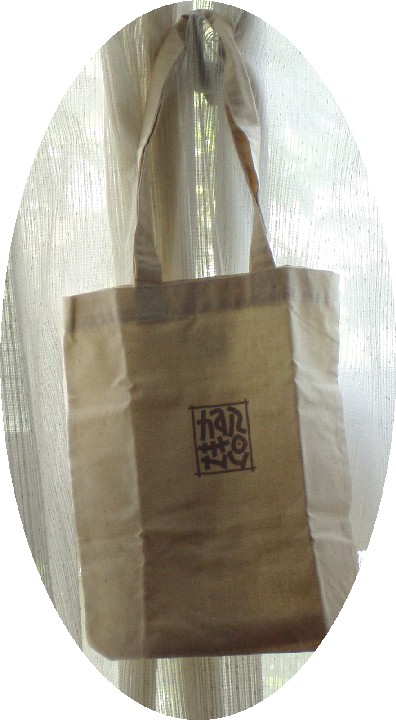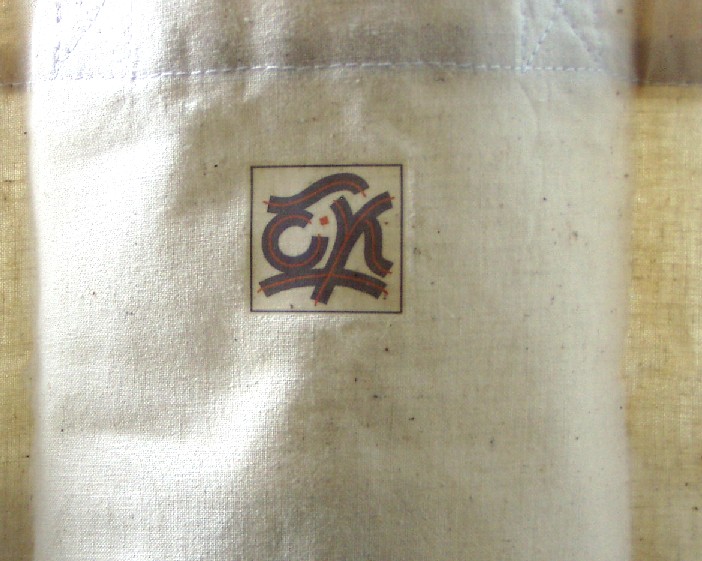
作品展の戦利品その1
京橋のギャラリークボタで行われている「アルファ・クラブ作品展」は、お天気のバックアップもあり、たくさんの人に訪れてもらっています。
ずいぶんと長い時間をかけて見てくださっている方が多く、作品の前で話しがはずんでいる様子を見ていると、何だか心が温かくなるものですね(外は暑いですが)…。
さて今回は、初試みでカリグラフィーを使ったグッズの販売も行っています。
ギャラリーショップと名づけた小さな空間は、みんなのアイデア満載の小さなものたちで一杯です!クオリティーは高いですよ!
この空間に足を踏み入れたら…あれもこれもと皆さん迷われて
手に一杯つかんでいる方も…。もしかして、ここが一番滞在時間が長かったりして…。
みんなが楽しそうに買っているので…裏方の私も最初はお客様優先で…と見守っていたのですが、とうとう手が…でてしまったの
でした〜。
カード類以外に、布物もたくさん出ています。Tシャツ、エプロン…。
そして、私が欲しかったのはこの小さな袋です。A4がちょうどおさまる程のかわいい袋です。
こういう大きさの袋はバッグにたたんで入れておけるし、便利なんですよね〜。しかもこの両面についたオリジナルのマークが素敵!
即、ゲットです。
そして、癒しの手書きのカード!
繊細な水彩カラーが涼を運んでくれそうですね〜。こちらも頂きました!
そうそう、福永由美子さんのカードも出てますよ〜!
戦利品第一弾でした!
昨日うかがって、素敵な作品群にため息をいくつもついてきました。
海外で活躍している作家さんたちの作品も直に見ることができて、
とてもよかったです。 作品集がほしいなぁ〜!と思いました。
もちろん、自分へのおみやげも忘れませんでした。
京橋まで来たのだからもう一息(結構しっかりの一息でした)、
と頑張って千葉市美術館まで遠征。
イギリスの「デザイナー・ブックバインダーズ」の作品、素敵でしたよ。
海外作品のあるスペースは、特別な空気が漂っていますよね。
ご覧になった方も圧倒された人が多かったです。
やはり長い間の経験、完璧なスキル、潔い線!
もう、ため息ものです。
千葉市美術館も行かれたのですね〜!私も早く行きたいと
思っています。…やっぱり遠征?…頑張ります。